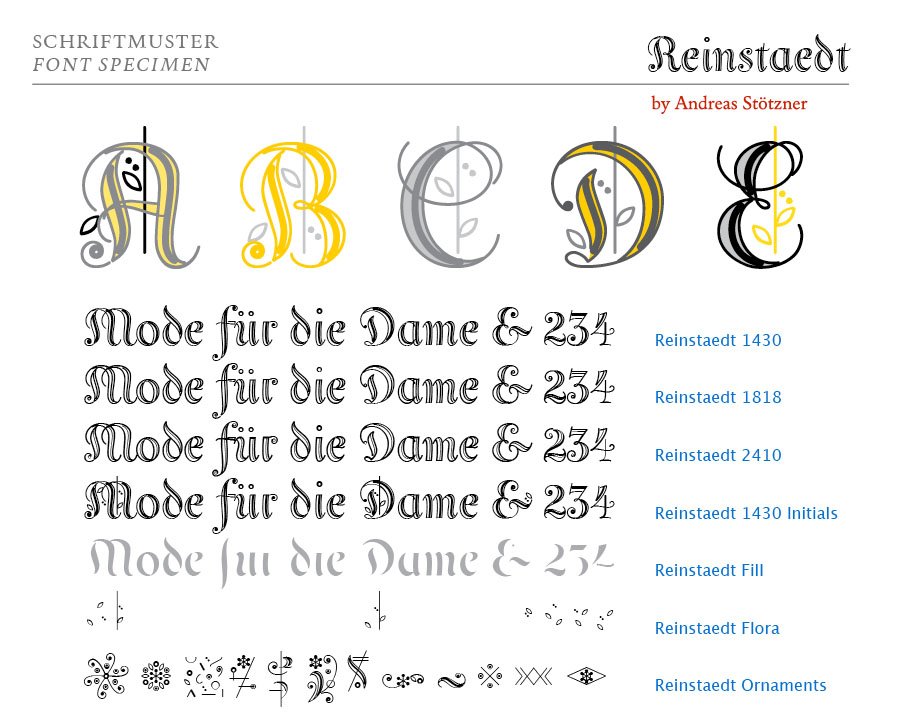
Reinstaedt (Andreas Stötzner)
Reinstaedt is a fancy new display font family designed from scratch by Andreas Stötzner.
The very first sketches were inspired during a holiday spent in remote Reinstädt of Thuringia (Germany). Though bearing a rather formal appearance Reinstaedt still shows its hand-drawn origin.
Reinstaedt gives a magnificent breath of fresh air to everything related to food, health, wellness, holiday – to the art of fine living.
Enhance your designs by creating enchanting headlines! You can design thrilling type variations by multi-colored overlaying and by combining with ornamental embellishments.
Witzig, die Schrift. Ein ganz klein wenig irritiert mich der geometrisch kreisrunde i-Punkt, da hätte ich etwas dynamischeres, besser an den Duktus angepaßtes erwartet.